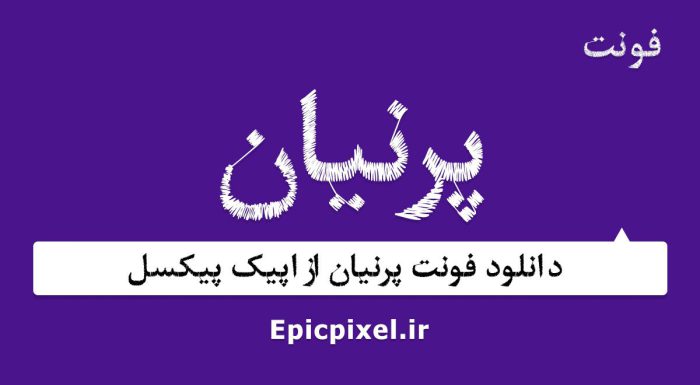
دانلود مجموعه کامل فونت Parnian فارسی Font اپیک پرنیان |
| ⭐ مجموعه فونت | دانلود فونت فارسی اپیک پرنیان بولد Font Parnian Bold |
| ⭐ توضیحات | مجموعه ای کامل از فونت های پرنیان و نسخه شبیه سازی شده بنام اپیک پرنیان فونت اپیک پرنیان با پشتیبانی از حروف فارسی ، انگلیسی / لاتین ، اعداد فارسی Fu Num |
دوست داشتنیه، کاش فونت های دیگه طرح دوختشون بود
برای متون با سایز بالاتر جلوه ی بهتر و بیشتری دارد. در سایز کوچیک فرق آنچنانی با فونت های معمولی و رایگان نداره.
عالی مثل کوک چرخ خیاطی میمونه
باورم نمیشه شبیه گلدوزی میمونه!!!
انگار فونت رو دوختن به بکگراند